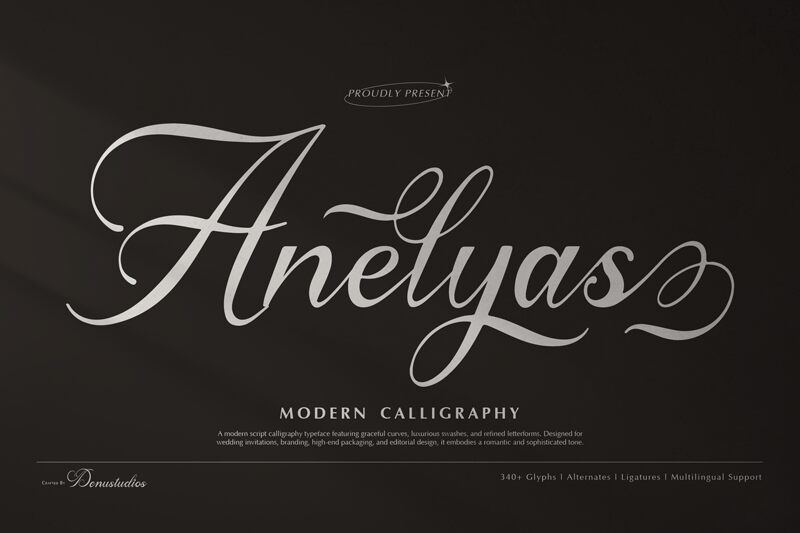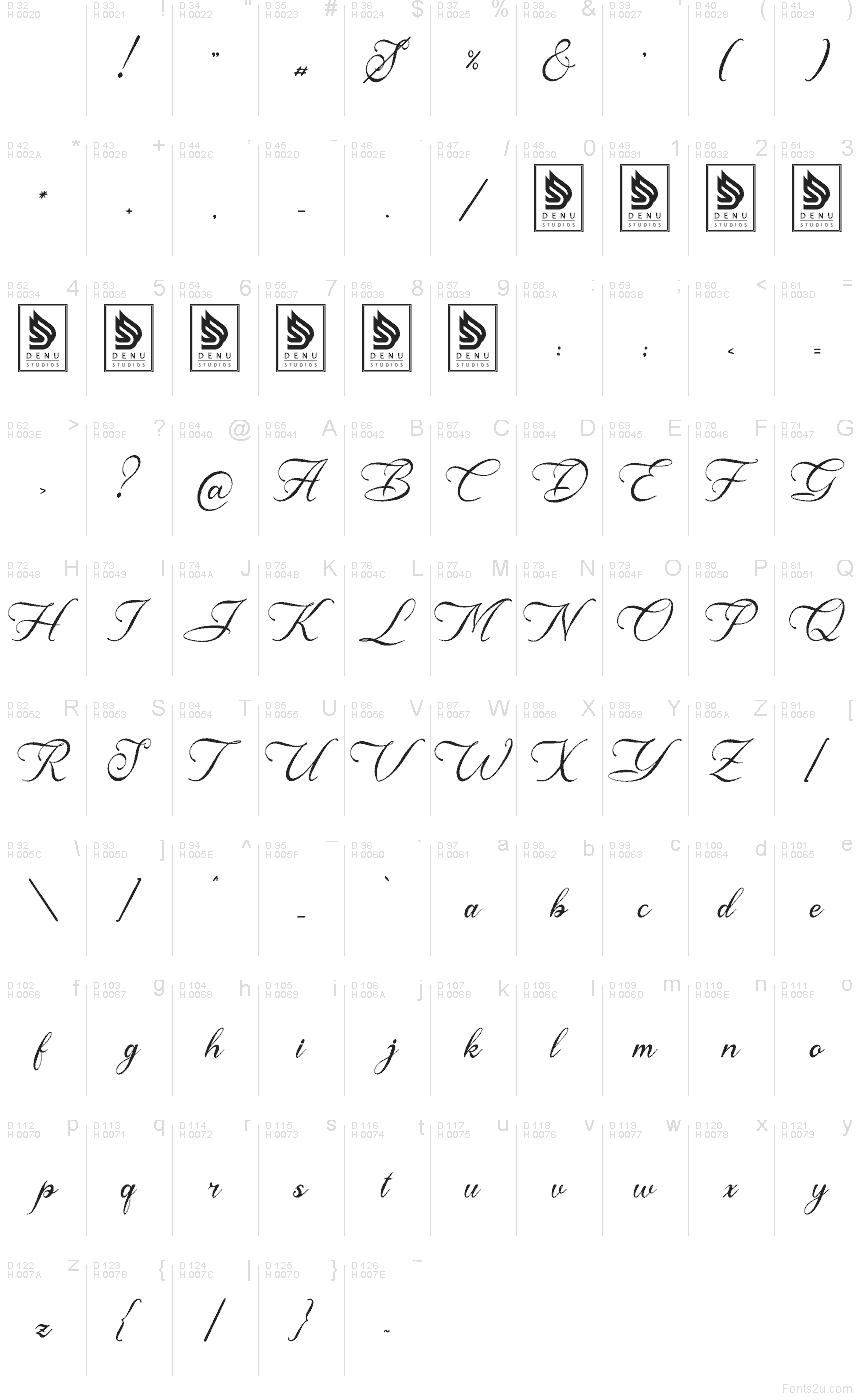
Anelyas de Denustudios es una tipografía caligráfica gratuita con un estilo formal y fluido, cargado de un toque romántico muy distintivo. Las letras combinan trazos finos con amplias florituras, especialmente en las mayúsculas iniciales y las formas descendentes, lo que le confiere un aire etéreo, elegante y solemne en lugar de informal.
Es ideal para papelería de bodas, branding de belleza, packaging de perfumes, titulares de portadas y logotipos de estilo firma donde se busque esa gracia manuscrita sin perder la sofisticación. Úsala para títulos cortos, invitaciones, monogramas o placas, donde sus curvas extendidas tengan espacio para respirar y convertirse en el centro de la composición.